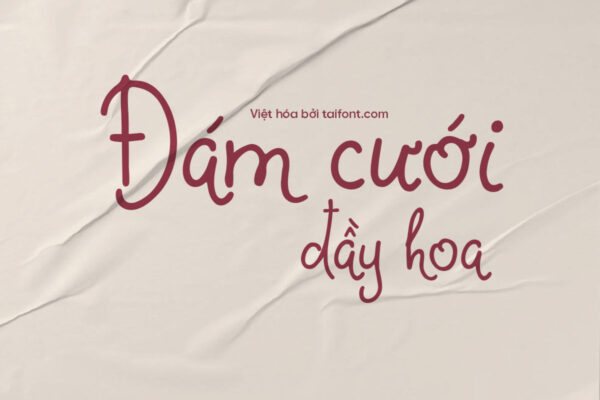
Font Việt hóa TF Swirly Delight là một font viết tay đẹp và độc đáo, lý tưởng cho các thiết kế thiệp cưới, thiệp mời. Với phong cách viết tay tự nhiên, font này mang lại cảm giác thân mật và ấm áp cho mọi thiết kế.
Ứng dụng của Font Việt hóa TF Swirly Delight
Font Việt hóa TF Swirly Delight có thể được sử dụng trong nhiều ứng dụng khác nhau, từ thiết kế thiệp cưới, thiệp mời đến thiết kế trang web và ứng dụng di động.
Cách sử dụng Font Việt hóa TF Swirly Delight
Lựa chọn font phù hợp
Để sử dụng Font Việt hóa TF Swirly Delight, bạn cần lựa chọn font phù hợp với thiết kế của mình. Font này có thể được sử dụng như font chính hoặc font phụ, tùy thuộc vào thiết kế.
Lợi ích của Font Việt hóa TF Swirly Delight
Font Việt hóa TF Swirly Delight mang lại nhiều lợi ích cho người dùng, bao gồm:
- Thiết kế đẹp và độc đáo
- Phù hợp với nhiều ứng dụng khác nhau
Sai lầm khi sử dụng Font Việt hóa TF Swirly Delight
Khi sử dụng Font Việt hóa TF Swirly Delight, bạn cần tránh một số sai lầm phổ biến, bao gồm:
- Sử dụng font không phù hợp với thiết kế
Font Việt hóa TF Swirly Delight